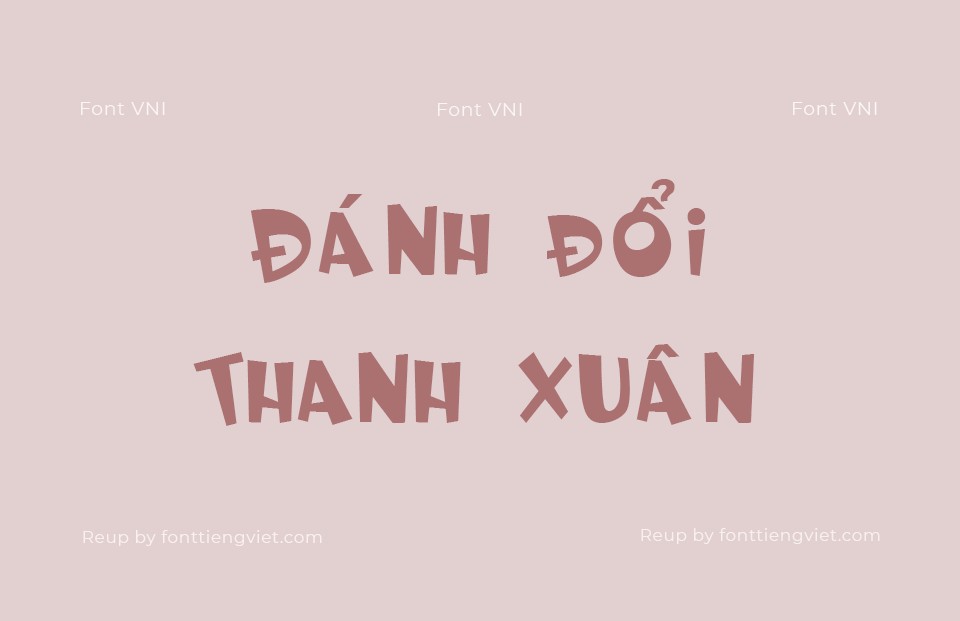
Font Việt hoá VNI Whimsy
Giới thiệu về Font Việt hoá VNI Whimsy
Trong thế giới đồ họa, việc lựa chọn một Font Miễn Phí phù hợp đóng vai trò quyết định đến linh hồn của tác phẩm. Font Việt hoá VNI Whimsy là một trong những bộ phông chữ mang phong cách ngộ nghĩnh, đáng yêu và đầy sự phá cách. Với các đường nét uốn lượn tự nhiên, bộ font này mô phỏng nét vẽ tay tinh tế, tạo cảm giác gần gũi và thân thiện. Đây là lựa chọn lý tưởng cho những dự án thiết kế hướng đến đối tượng trẻ em, học sinh hoặc các ấn phẩm mang tính giải trí cao.
Ưu điểm nổi bật của Font Việt hoá VNI Whimsy
Phong cách thiết kế độc đáo
Đúng như tên gọi Whimsy, bộ phông này mang lại sự bay bổng và không gò bó. Các ký tự được tạo hình không đối xứng, tạo nên nhịp điệu vui tươi cho dòng văn bản. Khi sử dụng Font Việt hoá VNI Whimsy, bạn có thể dễ dàng làm nổi bật các tiêu đề sách, thiệp mời hay các bảng hiệu trang trí lớp học. Sự linh hoạt trong đường nét giúp font chữ này không bị khô cứng như các kiểu chữ serif truyền thống.
Khả năng tương thích tốt
Mặc dù thuộc bảng mã VNI cũ, nhưng phiên bản Việt hóa đã giúp người dùng dễ dàng gõ tiếng Việt có dấu một cách mượt mà. Font chữ này hỗ trợ tốt trên các phần mềm thiết kế phổ biến như Photoshop, Canva hay CorelDraw. Bạn có thể kết hợp nó với các màu sắc rực rỡ để tạo nên những sản phẩm truyền thông ấn tượng, thu hút ánh nhìn của người xem ngay từ lần đầu tiên.
Kết luận và hướng dẫn sử dụng